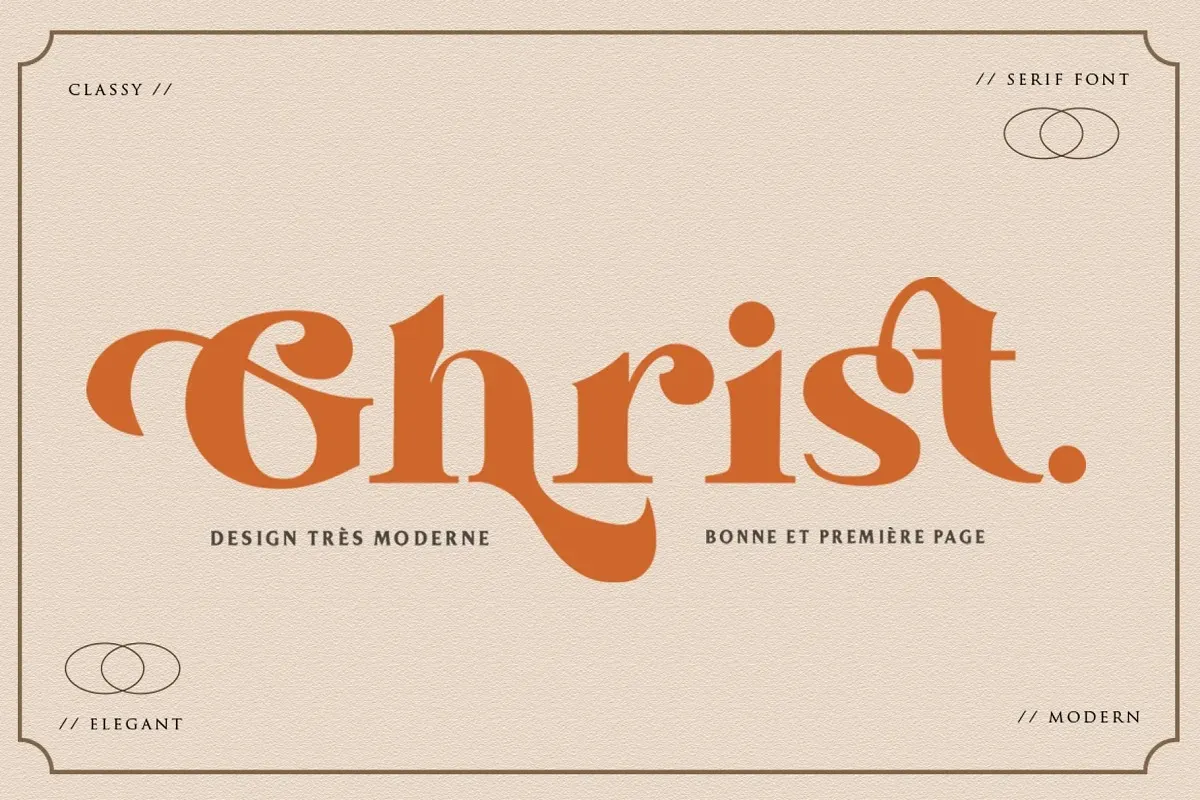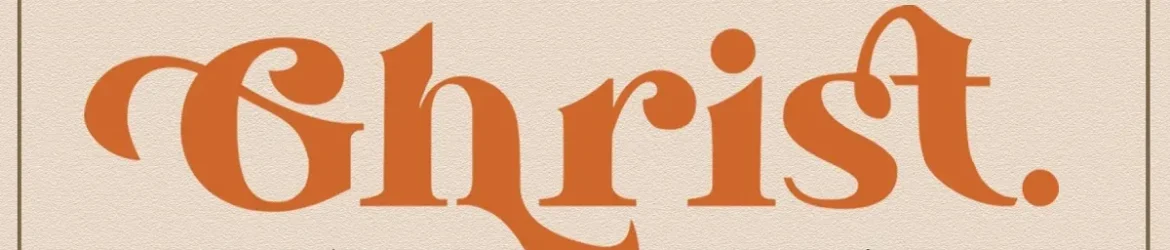
A Ghrist Font é uma tipografia serif que traz ao seu trabalho algo inovador e clássico. Ela foi projetada para oferecer sua própria identidade visual, com um estilo único e visão moderna, ideal para qualquer projeto de design. Além disso, a fonte inclui múltiplas alternativas de caracteres, facilitando o processo de trabalho sem deixar de proporcionar um toque divertido ao tipo de texto. Essa característica torna-a uma opção versátil e prazerosa para quem busca personalidade em seus projetos de design. A Ghrist Font é perfeita tanto para aqueles que buscam um ar mais clássico, quanto para designers que desejam dar um toque inovador a suas criações, oferecendo uma experiência de trabalho eficiente e emocionante.